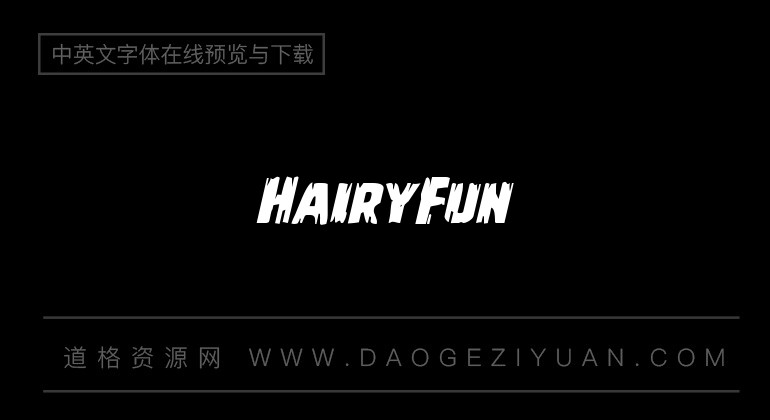
? HairyFun 字体是一款美观而有趣的手写字体,由具有丰富经验的设计师开发而成。它非常适合用于商业和个人项目,可以给任何文字添加一种活泼、有趣的视觉效果。HairyFun 字体具有自然的手写风格,它可以帮助你为你的设计添加一些轻松的和谐感。内容介绍
HairyFun是一款非常不错的手写艺术字体,具有很好的视觉感,适合于文化类的宣传设计、商业类品牌的广告和产品包装设计以及个性化文字排版等较多场景。